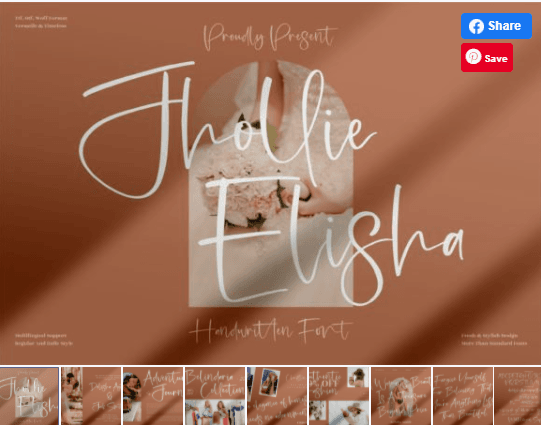
Jhollie Elisha Font
Jhollie Elisha - стильный и элегантный шрифт. Поддайтесь этому восхитительному стилю и используйте его для создания великолепных свадебных приглашений, красивых канцелярских принадлежностей, ярких постов в социальных сетях и многого другого!